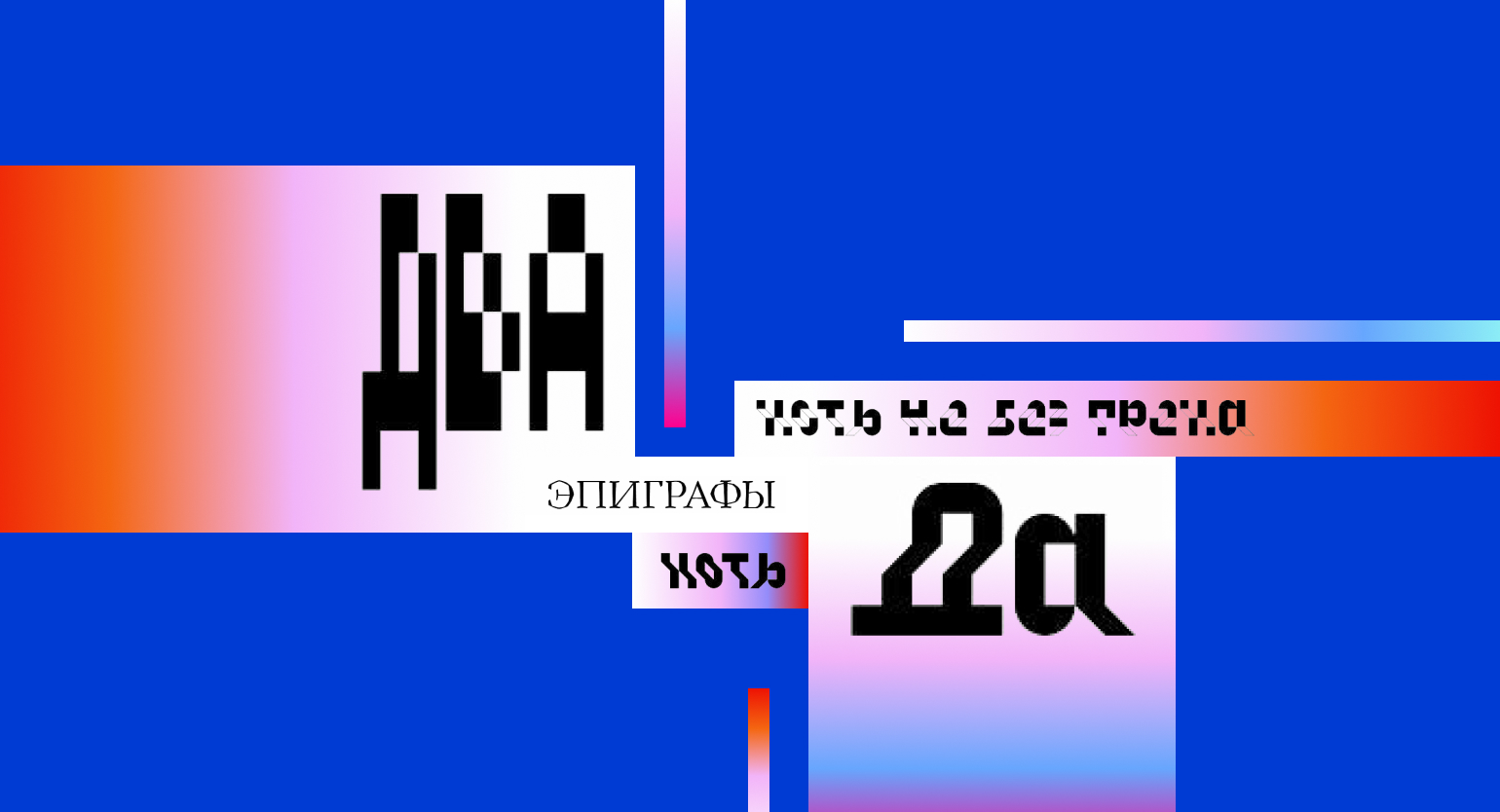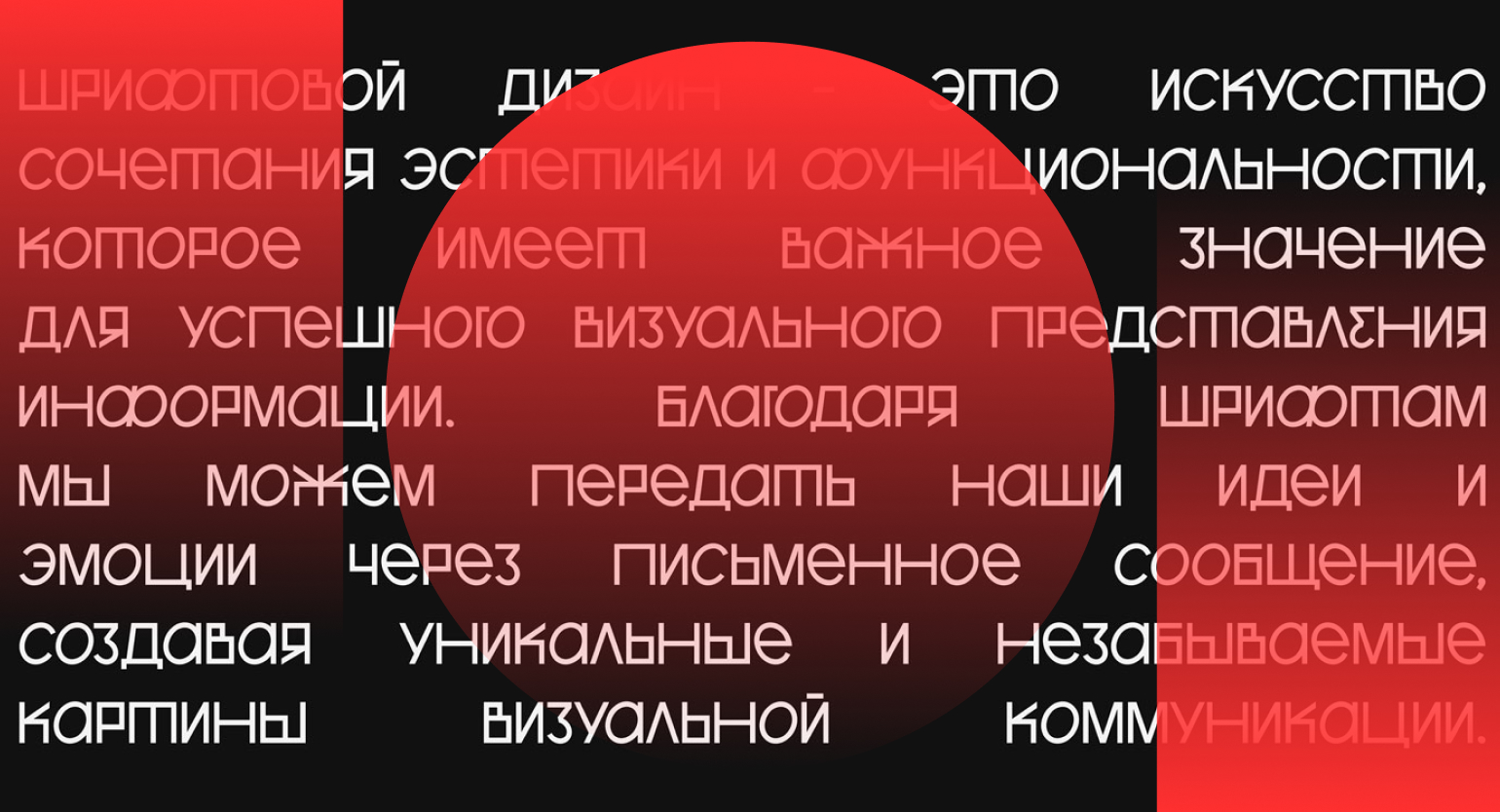
24 новых шрифта с кириллицей
Бесплатные и платные для дизайна в 2025 году.
Собрали актуальные проекты от шрифтовых дизайнеров: все качественные, с кириллицей, не примелькались в массовом дизайне и выглядят свежо.
Бесплатные шрифты
1. Lanze
Авторы — Дмитрий Гренев и Родион Илюхин.
Стиль: вариативный акцидентный гротеск с двумя осями — контрастом и насыщенностью штриха. Выразительный характер шрифта проявляется в острых срезах и контрастных формах.
Состав: латиница и кириллица, цифры, знаки пунктуации. Четыре основных начертания (называются нестандартно: Pike, Spear, Scythe, Halberd) и есть возможность тонкой настройки промежуточных начертаний.
Для чего подходит: идеально — для музыкальных афиш, титров в кино, фешен-брендов и технологических стартапов. Благодаря вариативности работает как в крупном размере для масштабных инсталляций, так и в вебе.
2. Shantell Sans
Авторы: студия ArrowType, кириллицу создавала Аня Данилова.
Стиль: рукописный шрифт с несколькими осями вариативности (насыщенность, наклон, формальность, прыгучесть, спейсинг). Comic Sans здорового человека!
Состав: расширенная латиница и кириллица. Обширная пунктуация, знаки валют и другие специальные символы.
Для чего подходит: идеален для айдентики детских брендов, афиш и открыток. Помогает делать инклюзивный дизайн: хорошо себя показывает в качестве доступного для дислексиков шрифта.
3. Akt
Автор — Дмитрий Гренев.
Стиль: неогротеск — много их не бывает. Несмотря на утилитарный жанр, имеет свой характер.
Состав: расширенная латиница и кириллица. Знаки пунктуации, альтернативные символы, регистрозависимые формы.
Для чего подходит: отличная рабочая лошадка на каждый день. Будет уверенно выглядеть как на странице книги, так и в качестве элемента большого фирменного стиля.
Шрифт в бета-версии, доработан, обновлён и дополнен в январе 2025-го.
4. Gehaks
Автор — Эмили Михайленко.
Стиль: акцидентная антиква с глиптальным характером, будто высеченная из камня. Главным вдохновением для её графики стали переходные гибриды готико-антиквы.
Состав: базовая латиница и кириллица. Пунктуация и набор стилизованных иконок.
Для чего подходит: Gehaks найдёт применение в титрах, журналах, брендинге с историческим привкусом и других сценариях, где ему дадут достаточно много места.
5. Cliamte Crisis
Авторы — Eino Korkala и Daniel Coull.
Стиль: акцидентный гротеск, который тает на глазах. Шрифт призван обратить внимание на проблему глобального изменения климата и убедительно показывает то, насколько близки эти изменения.
Состав: расширенная латиница, базовая кириллица и даже хангыль (корейский). Пунктуация, альтернативы и специальные символы.
Для чего подходит: в первую очередь шрифт создан для экоактивистских проектов, однако его жирное начертание хорошо себя показывает и вне этой концепции.
6. Libre Franklin
Авторы — ImpallariType, кириллицу разрабатывал Алексей Ваняшин.
Стиль: ранний американский гротеск, вдохновлённый классическими работами Морриса Фуллера Бентона.
Состав: расширенная латиница, кириллица. Пунктуация, валюты и специальные символы.
Для чего подходит: идеальный выбор для проектов, где есть отсылки к американской эстетике. В маленьких кеглях может служить как текстовый шрифт, а в увеличенном размере демонстрирует свои намеренные шероховатости гротесков той эпохи.
7. Drabina
Автор — Марк Ломакин.
Стиль: экспериментальный шрифт, созданный во время практики в сообществе Playfaces. Массивный и геометричный, но при этом подвижный за счёт игры модулей в трёхмерном пространстве. Особенность Drabina — отсутствие выносных элементов.
Состав: поддерживает базовые кириллицу и латиницу и доступен в двух начертаниях — solid и outline.
Для чего подходит: реклама, афиши, плакаты. Drabina любит много места и теряет свой трёхмерный шарм в маленьких размерах.
8. P95-Cyr
Автор — Евгений Арцебасов.
Стиль: акцидентный модульно-пиксельный шрифт.
Состав: базовая латиница и кириллица. Пунктуация и немного альтернативных символов.
Для чего подходит: из-за особенностей построения рекомендуется использовать в очень больших кеглях. Однако в правильных руках может стать идеальным инструментом, чтобы привлечь внимание к тексту.
Платные шрифты с кириллицей